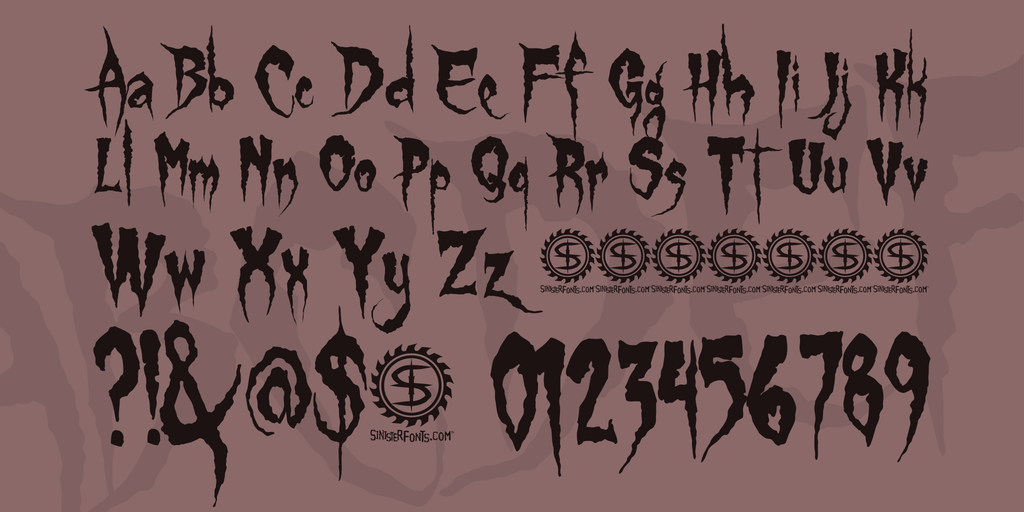
11 бесплатных шрифтов Хэллоуина
Загрузите эти лучшие бесплатные шрифты Хэллоуина
Эти бесплатные хэллоуинские шрифты – лучшие жуткие, жуткие и даже глупые шрифты, доступные онлайн. Они не будут стоить вам ни копейки за скачивание, установку и использование для вашего следующего проекта на Хэллоуин.
Эти бесплатные шрифты Хэллоуина – отличный способ настроить приглашения на Хэллоуин, украшения и все остальное, что может прийти в голову.
Calaveras Бесплатный Хэллоуин Шрифта от Гарольда Шрифты
Вы будете любить пузырьковый шрифт, покрытый черепами этого бесплатного шрифта Хэллоуина. Это отличный дизайн, который также идеально подходит для проекта Day of the Dead.
Когда вы загрузите шрифт Calaveras Halloween, вы получите шрифт Calaveras в верхнем, нижнем регистре, цифры, символы и специальные символы.
Halloween Spider Бесплатный Хэллоуин Шрифта Клода
Этот бесплатный шрифт Хэллоуина показывает ползущих пауков и их паутину, окружающую заглавные буквы.
Этот бесплатный шрифт на Хэллоуин отлично сочетается с некоторыми бесплатными клипами на Хэллоуин для создания собственных печатных приглашений на Хэллоуин.
Creepsville Бесплатный Хэллоуин Шрифт Тони О’Фаррелл
Creepsville – похожий на привидение бесплатный хеллоуинский шрифт, напоминающий мне о медленно капающей крови или слизи. Это будет отлично смотреться на любом из ваших проектов на Хэллоуин.
Creepsville поставляется заглавными и строчными буквами, а также несколькими символами.
Wild Wood Бесплатный Хэллоуин шрифт от студии Jester Font
Wild Wood – отличный бесплатный шрифт для Хэллоуина, в котором бесплодные ветви крутятся со всех сторон вашего сообщения на Хэллоуин.
Этот бесплатный шрифт Хэллоуин имеет заглавные буквы и цифры.
Джек Лантерн BB Бесплатный Хэллоуин шрифт от Blambot
Этот бесплатный шрифт Хэллоуина воспроизводит сказку о Сонной Лощине с ее жуткими зубчатыми изгибами.
Вы можете использовать этот бесплатный шрифт Halloween практически на любом из ваших проектов, и он будет отлично смотреться.
Очаровательный бесплатный шрифт Halloween от GemFonts
Помните старый сериал Зачарованные? Ну, вот откуда появился этот бесплатный шрифт Halloween.
Этот пышный бесплатный шрифт Halloween немного более элегантен, но все же немного ползучий.
Я вижу, что это действительно хорошо работает для приглашения на вечеринку.
Groovy Ghosties Бесплатный Хэллоуин шрифт от Typodermic Fonts
Шрифт Groovy Ghosties free Halloween содержит тонких призраков, которые выглядят так, словно они исчезнут на ваших глазах.
Этот бесплатный шрифт Halloween идеально подойдет для детей, но он действительно подойдет для любителей вечеринок на Хэллоуин любого возраста.
Бесплатные колючие чернила для Хэллоуина от Матье Кломп
Barbed Ink – это бесплатный шрифт Halloween, который выглядит как более гладкая версия колючей проволоки.
Это бесплатный хеллоуинский шрифт, который как-то немного сексуально и немного жутко одновременно.
Jack O Бесплатный Хэллоуин Шрифта Клода
Ни один список бесплатных хеллоуинских шрифтов не был бы полным без такого шрифта, как этот, на котором изображены фонарики с надписью «Jack o ‘», излагающие ваше сообщение.
Этот бесплатный шрифт Halloween содержит прописные и строчные буквы, которые вы можете использовать для своего проекта Halloween.
CF Halloween Font от CloutierFontes
Буквы в шрифте CF Halloween на Dafont залиты кровью и переполнены паутиной. «Я» – это мрачный жнец, а «О» – это гнездо О’Лантера.
Этот шрифт доступен только для заглавных букв и цифр. Коммерческая лицензия доступна для покупки.
Жуткий Хэллоуин от шрифтов Мисти
Вот уникальный шрифт Хэллоуина, который представляет собой шрифт мазка с привидением. Основные моменты включают звезду, летучую мышь, большой призрак и маленький призрак.
Этот шрифт доступен для прописных и строчных букв, цифр и набора специальных символов.
У меня было достаточно свободного времени в Бордо, поэтому я зарисовывал кое-что в свою записную книжку. В 1944 году я записал туда «Junggesellentext» Ганса фон Вебера (Hans von Weber), который через 50 лет был воспроизведен в оригинальном размере, когда компания Linotype представляла гарнитуру Zapfino. Удивительно, но тогда мне не нужны были очки или увеличительное стекло, чтобы рисовать такие маленькие буквы. У меня было превосходное зрение!